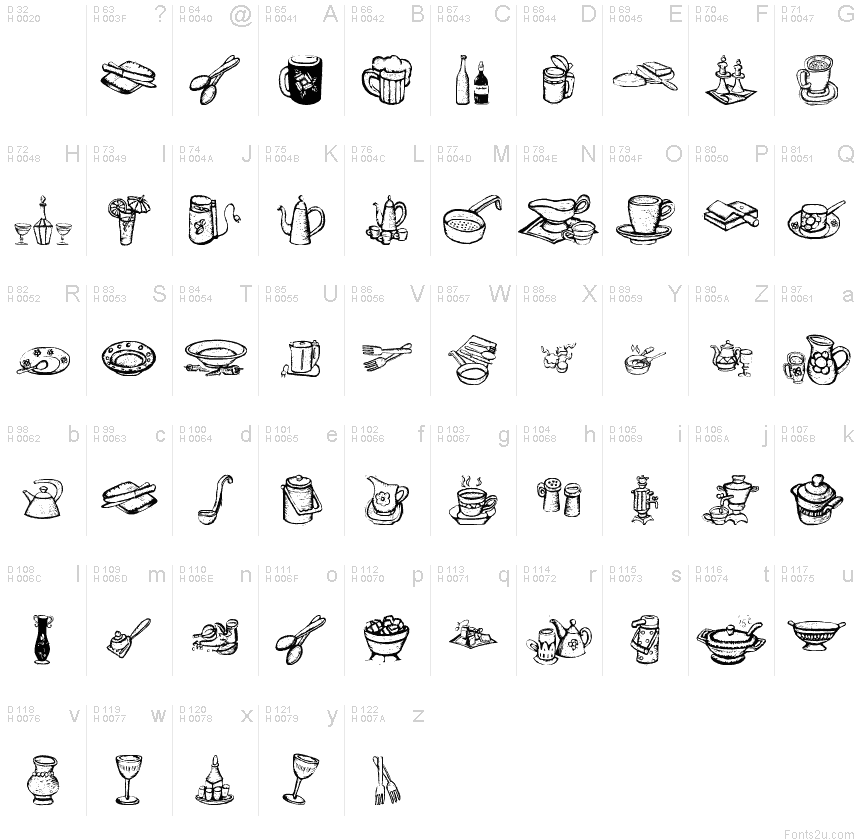
PrositBats от M. Klein — это бесплатный шрифт с дингбатами, нарисованный от руки. Его кухонно-барная тематика создает уютную атмосферу старинной таверны. Набор состоит из набросочных контуров, штрихов, напоминающих гравюру, и узнаваемых предметов: пивной кружки, чайника, ложек, кофейника, самовара и сэндвича. Всё это придает шрифту домашний, «крафтовый» вид, в противовес излишней глянцевости.
Благодаря этому шрифт отлично подойдет для оформления меню, пивных этикеток, флаеров для кафе, карточек с рецептами или заголовков фуд-блогов, где небольшая группа иконок поможет быстро передать суть. Он также будет уместен на печатях для упаковки или титульных карточках, которым нужно добавить нотку деревенского гостеприимства: рисунки выглядят так, будто их достали прямо из кладовой.